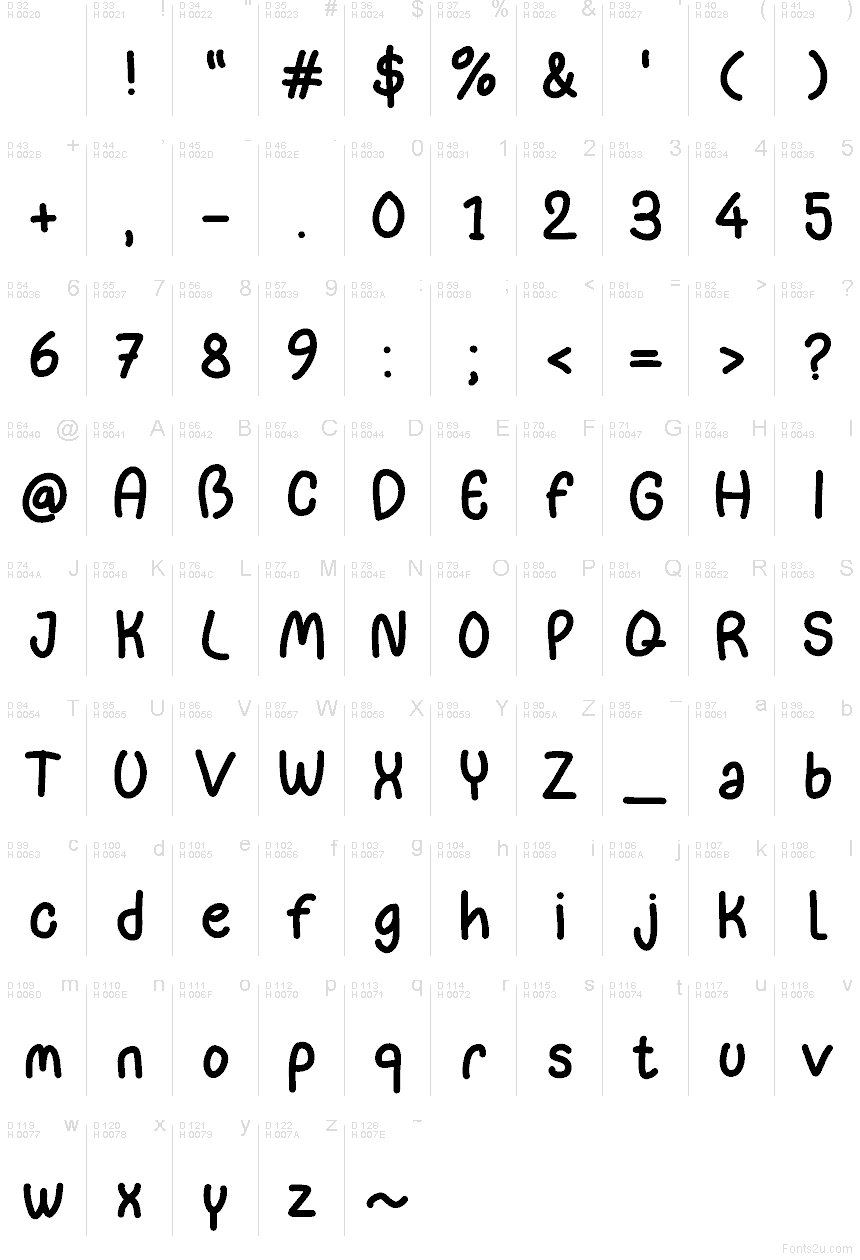
Oahyou Minna Regular
Oahyou Minna — це безкоштовний мультяшний шрифт із м’якими заокругленими лініями та рукописним стилем, що ідеально підходить для дітей. Нерівні вигини та невимушений ритм надають дизайну дружнього, «казкового» вигляду, не втрачаючи при цьому чіткості.
Oahyou Minna — це безкоштовний шрифт, який чудово підходить для дитячих книг, шкільних плакатів, заголовків у коміксах, запрошень та веселих логотипів. Заокруглені форми та вільний стиль малювання також доречні для вітальних листівок, креативного пакування та графіки для соціальних мереж, де важлива тепла та неформальна атмосфера.